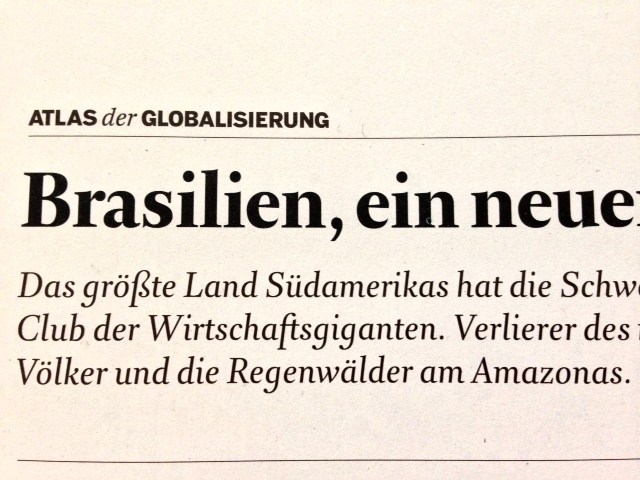
Schrift der "le monde diplomatique"
weiß jemand von euch, welche Schrift im Magazin "LE MONDE diplomatique"
für die Sublines verwendet wird? Ich dachte im ersten Moment an die DTL Paradox.
Aber das ist sie leider nicht. Freue mich über eure Tips.
Hier noch ein Bild dazu:
genau  :gimmifive: . Allerdings wird dort als Kursive die Arnhem Blond Italic verwendet, die sieht aber etwas anders aus, siehe z. B. das k.